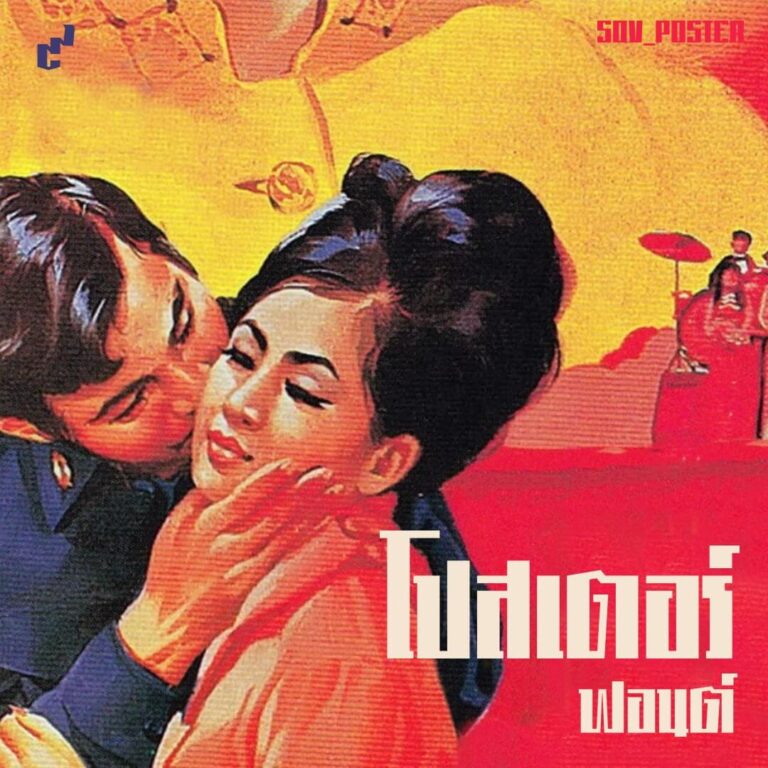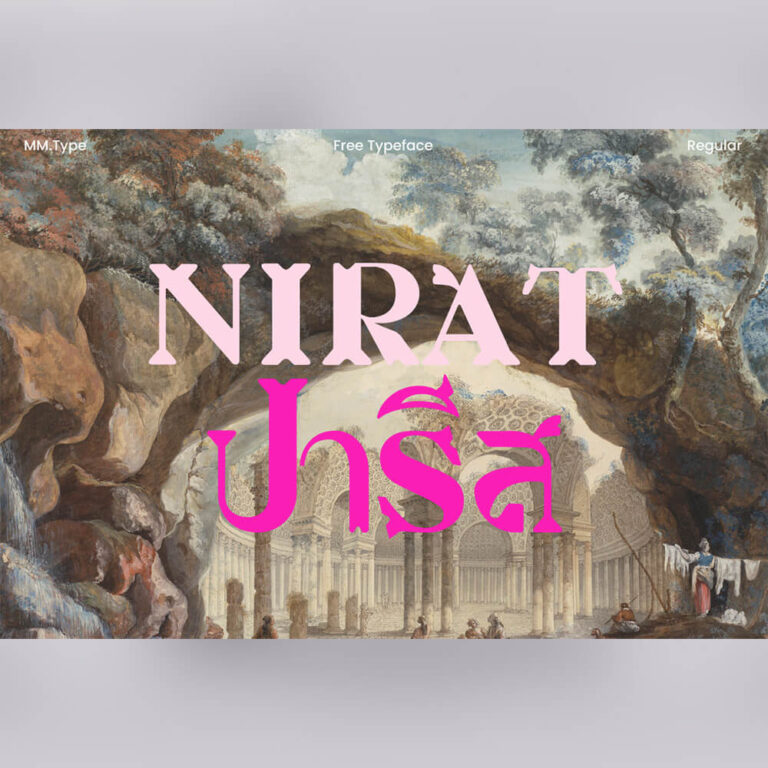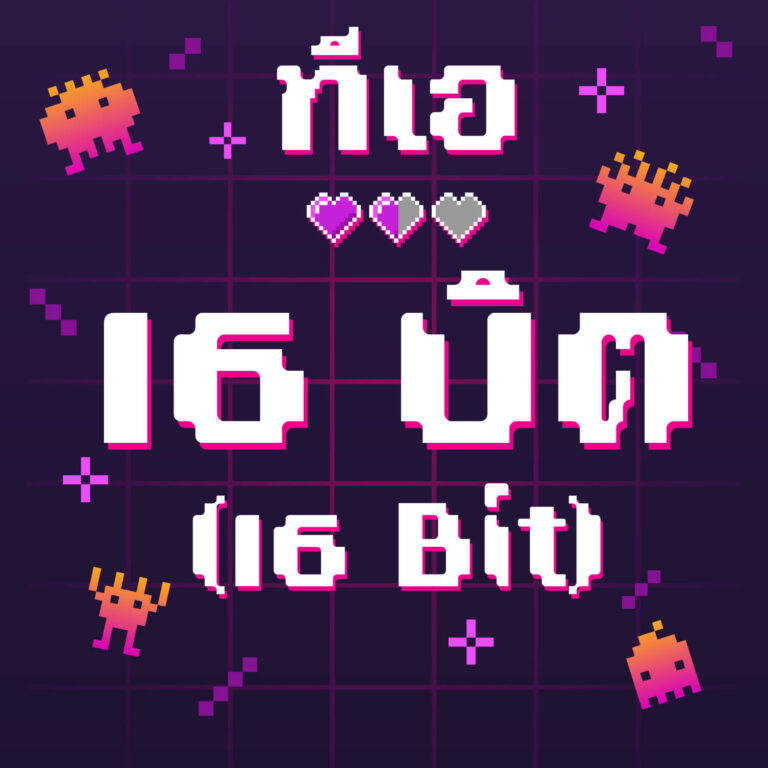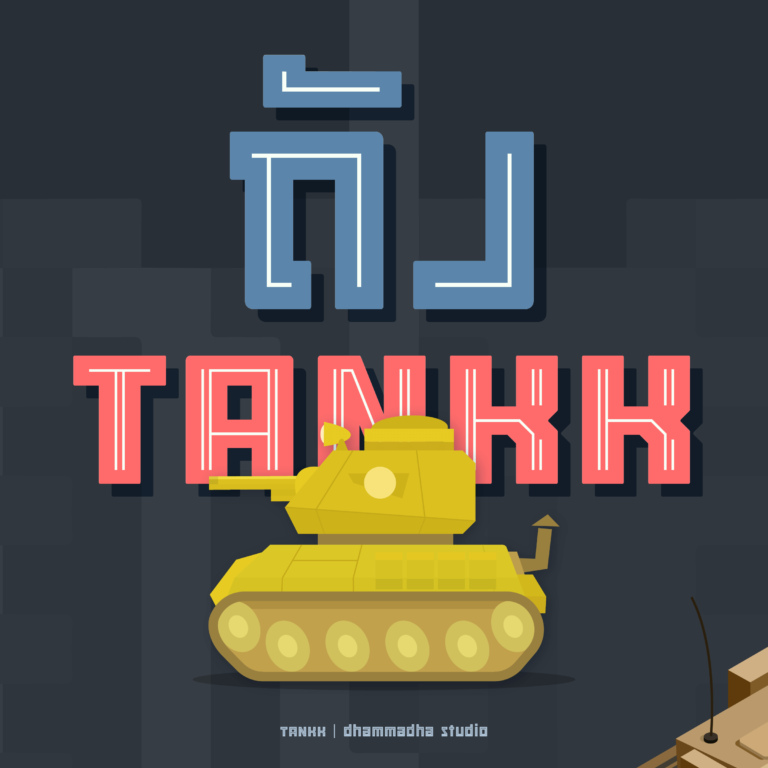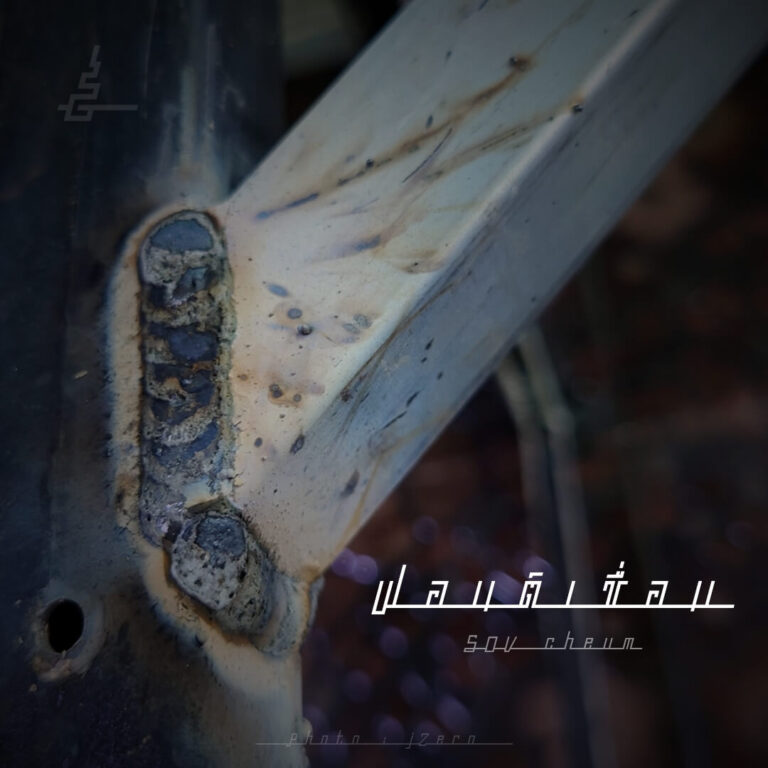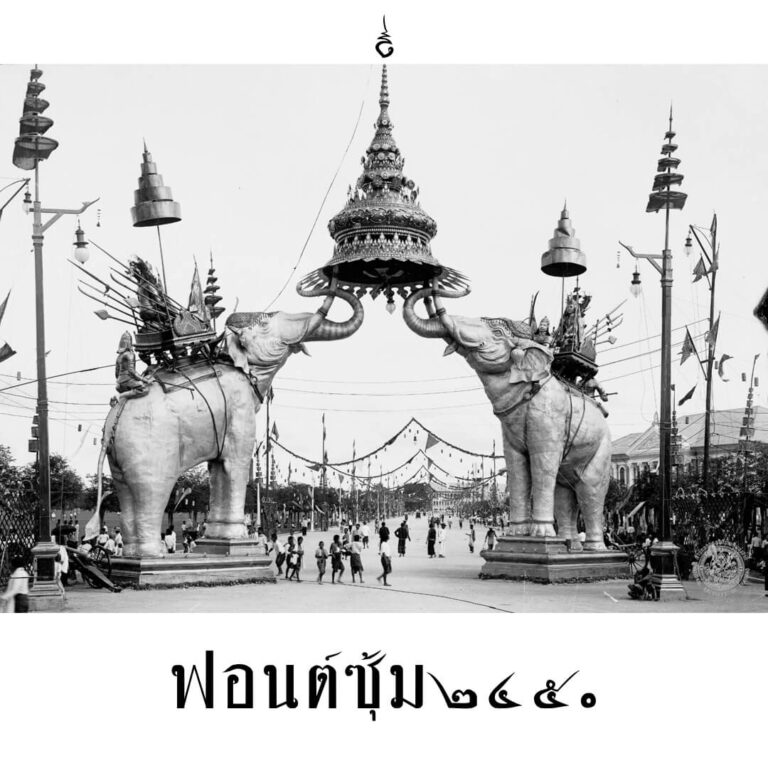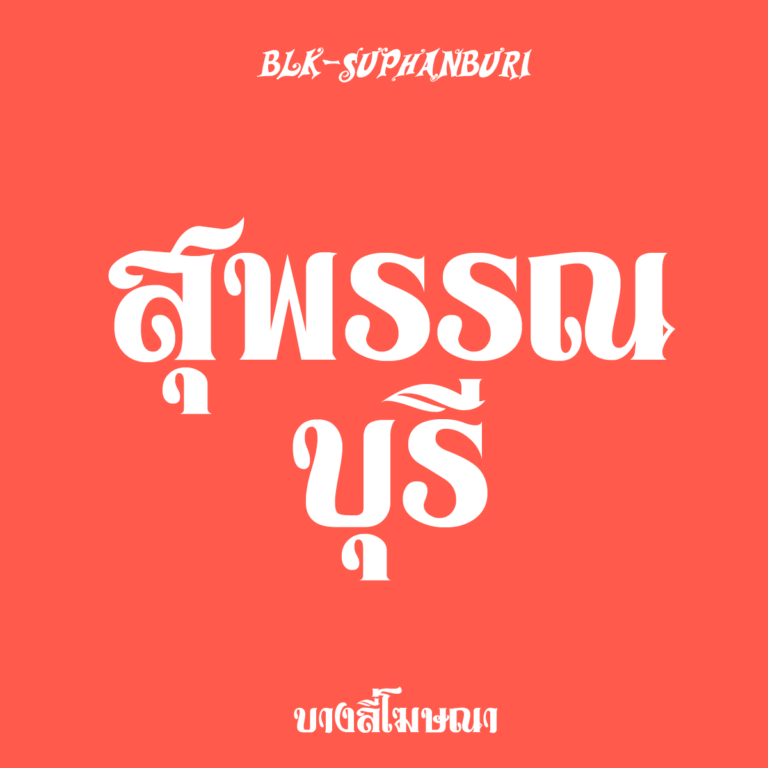
DM Gumble (ดีเอ็ม กัมเบิ้ล)
ฟอนต์แนว Retro ที่ผสมผสานให้มีความน่ารัก ทำให้นึกย้อนไปตอนที่ยังเป็นเด็กๆ
ฟอนต์ป้ายสถานีรถไฟจากภาพเก่าๆ รุ่นตัวอักษรสีขาวบนพื้นสีเข้ม ไล่เก็บตัวอักษรจากรูปเก่าๆ จนเกือบครบ ตัวที่เหลือก็เดา ไม่ได้อ้างอิงเอกสารใดๆ
ชุดฟอนต์พาดหัว เก่า และเก๋าโดดเด้งแรงบันดาลสุดหัวใจ จาก ปก LP แม่นางนกขมิ้นของ คุณสมยศ ทัศนพันธ์ ศิลปินเพลงไทยลูกทุ่งรางวัลแผ่นเสียงทองคำพระราชทาน จากบทเพลง “ช่อทิพย์รวงทอง”
ที่มาของฟอนต์ คือลายมือเขียนบรรยายภาพในหนังสือพิมพ์uvSOV
ฟอนต์ 7บิต แนวคิดมาจาก ASCII art text banner ที่นิยมใช้บนระบบ unix, linux ตั้งแต่ยุคที่ ASCII รองรับแค่ 7 บิต โดยเลือก font Slant เป็นต้นแบบ แล้วดัดแปลงเป็นภาษาไทย ทำ kerning โดยจำเป็น
ฟอนต์โรงหนัง อักษรแขวนหน้าโรงหนัง ที่บางครั้งตัวเกี่ยวหลุดไป แอบห้อยต่องแต่ง
ฟอนต์โค้ง ได้แนวทางมาจากการเอาส้อมจิ้มหมึกแล้วลากเส้น พอถึงจุดหักข้อ ก็ปักจุดหมุน หรือทิ้งโค้ง แล้วค่อยลากเส้นต่อ โค้งไปโค้งมาว่างั้น
ฟอนต์นี้ทำเนื่องจากกระทู้ถามฟอนต์ แต่จากหลักฐานปีที่ซ่อมสร้างเสร็จในภาพ ยังไม่น่าจะมีการทำฟอนต์แบบปัจจุบัน ยิ่งหาข้อมูลยิ่งพบความน่าสนใจ จนนำไปสู่การทำฟอนต์จนได้
ฟอนต์ตามคำขอ.. ถามว่าสนใจทำฟอนต์นี้ไหม ส่งรูปปี ๒๔๕๐ มาให้ ๑ รูป จากนั้นก็เริ่มหารูปจากใน internet พบว่าเป็นปีที่ ร.5 เสด็จกลับจากยุโรปครั้งที่ 2 มีการทำซุ้มรับเสด็จไว้ใหญ่โตน่าตื่นตา จึงตั้งชื่อฟอนต์ว่า “ซุ้ม”
ตอนแรกจะทำฟอนต์ขีดเส้นใต้ แต่เปลี่ยนเส้นใต้มาเป็นเส้นเชื่อมดีกว่า ..หวานดี
ชุดฟอนต์ย้อนวัย เข้มแข็ง บึกบึนใช้พาดหัว เป็น Display Font ได้กระแทกสายตาอย่าใช้เป็นเนื้อความ Text Font ..อันนี้ไม่เหมาะ
เป็นฟอนต์แนวเกมพิกเซล เรโทร ย้อนยุค นะครับ ฟอนต์นี้น่าจะถูกใจสายเกมยุคเก่าๆ หน่อย โดยผมเริ่มต้นทำตัวฟอนต์จากเว็บ fontstruct.com นะครับ เสร็จแล้วจึงเซฟมาทำงานต่อในโปรแกรมทำฟอนต์อีกที
นิราศปารีส เป็นฟอนต์ที่ได้แรงบันดาลใจมาจากรูปแบบของสถาปัตยกรรม ในเมืองปารีส เช่นตัวฐานหอไอเฟล โครงสร้างมหาวิหารนอตราดาม และรูปปั้นบนมหาวิหาร
ฟอนต์จากตัวอักษรในโปสเตอร์ช่วงปี ๒๕๐๑ – ๒๕๑๔ ดูเป็นระเบียบเรียบร้อยแต่ลูกเล่นเพียบ ตัวอักษรใช้แคบกว้างสลับกันไปตามความเหมาะสม สระบนก็กว้างแคบตามไปด้วย เวลาใช้ให้เอา bold มาผสมกับ regular นะครับ
เป็นฟอนต์ที่เล่นกับน้ำหนัก หนา-บาง ของเส้นนะครับ ไอเดียเริ่มต้นมาจากฟอนต์ของต่างประเทศ ชื่อ Magazine เห็นแล้วรู้สึกชอบการเล่นกับน้ำหนัก จึงลองๆ วางเส้นหนักเบาสลับๆ เป็นภาษาไทยดู ก็ได้ออกมาประมาณนี้ ในอนาคตว่าจะลองใส่หัวกลม หัวทึบ เพิ่มเติมเป็นฟอนต์ตัวต่อๆ ไปนะครับ
เป็นฟอนต์ตามคำขอ จากเพื่อนผู้เชี่ยวชาญภาพเก่า เรื่องเก่าๆ ในเมืองไทย… ถามว่าเคยทำฟอนต์ราชดำเนิน ตัวกลมๆ หรือยัง แล้วส่งรูปให้ดู ผมเห็นว่าเก๋ไก๋ดี ก็เลยลองทำตามแบบในรูปเก่าๆ ที่เพื่อนส่งมาให้ดูครับ นำไปใช้ได้ตามสะดวก